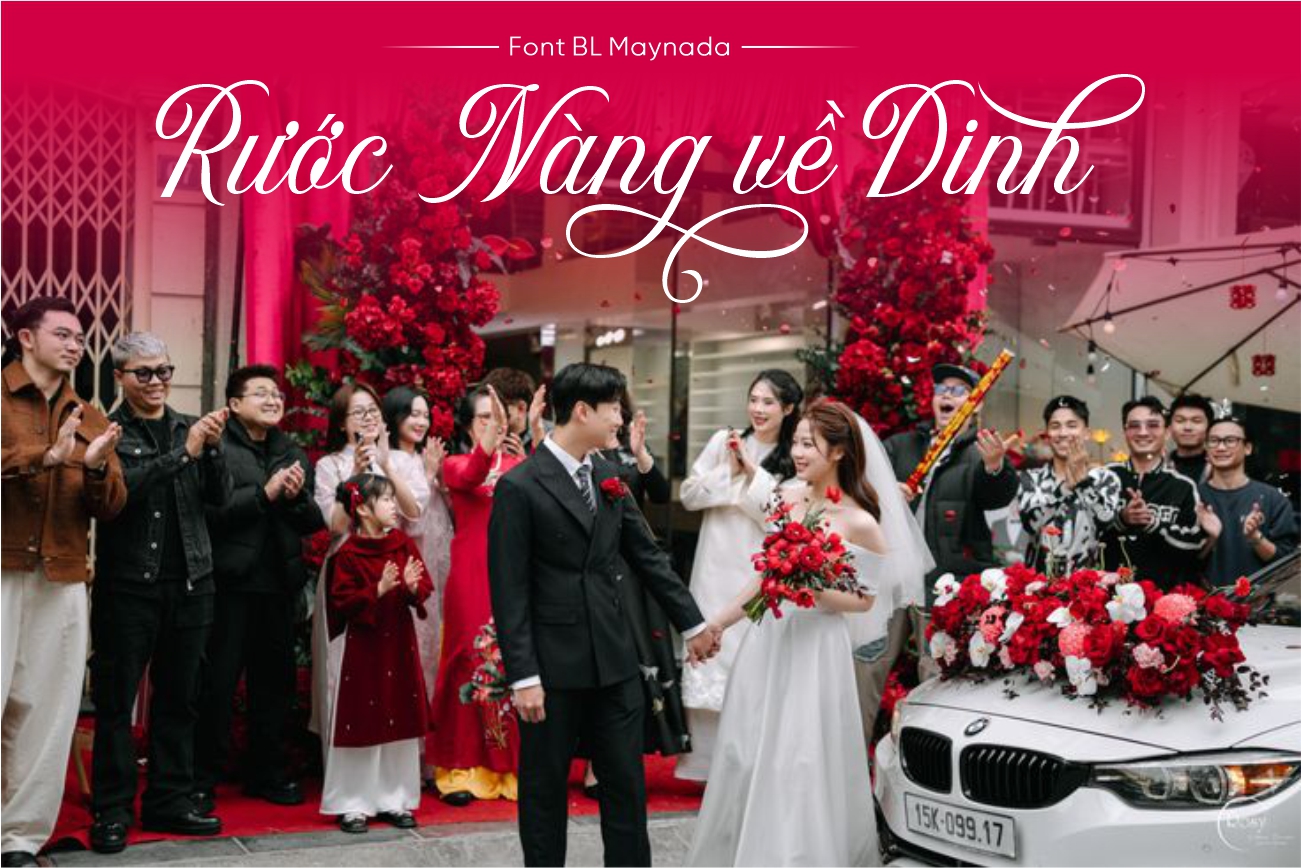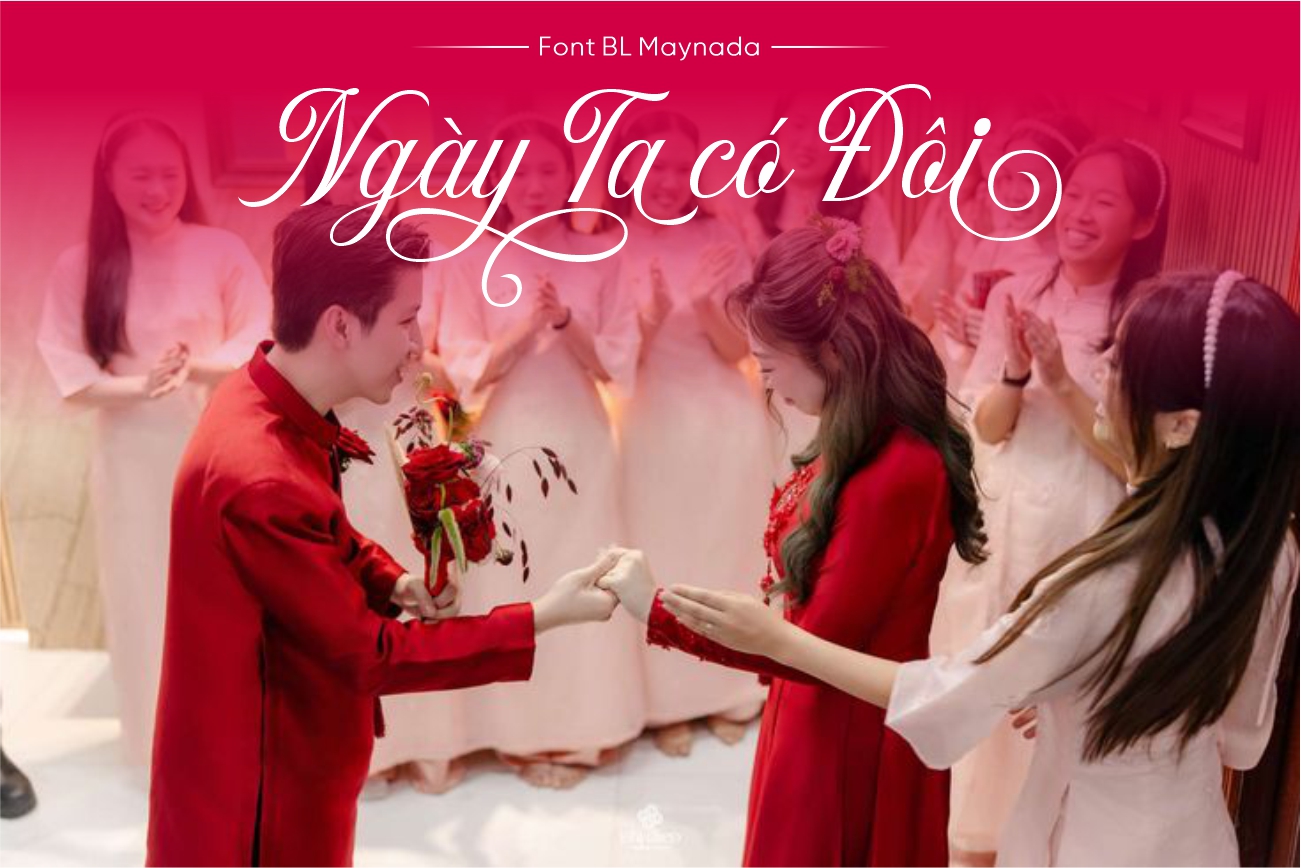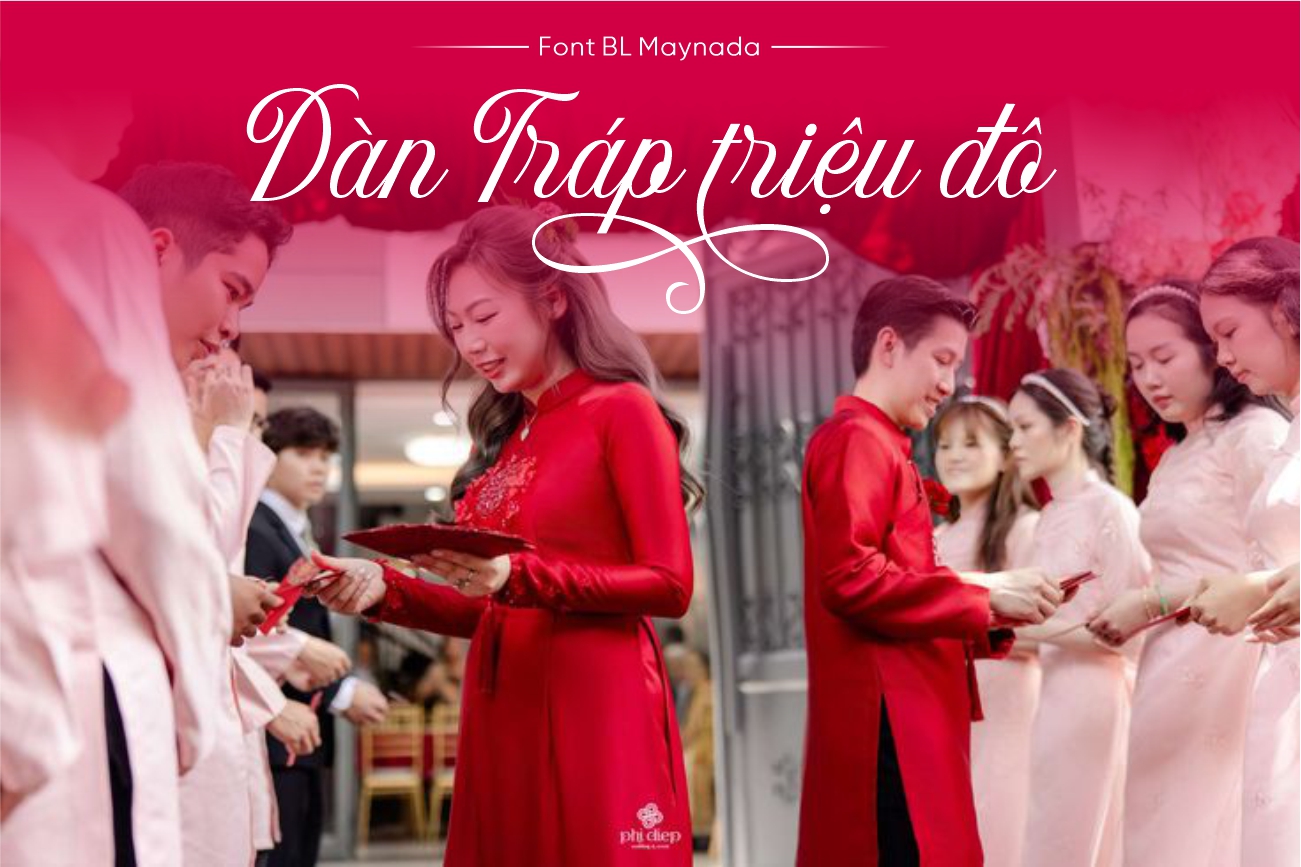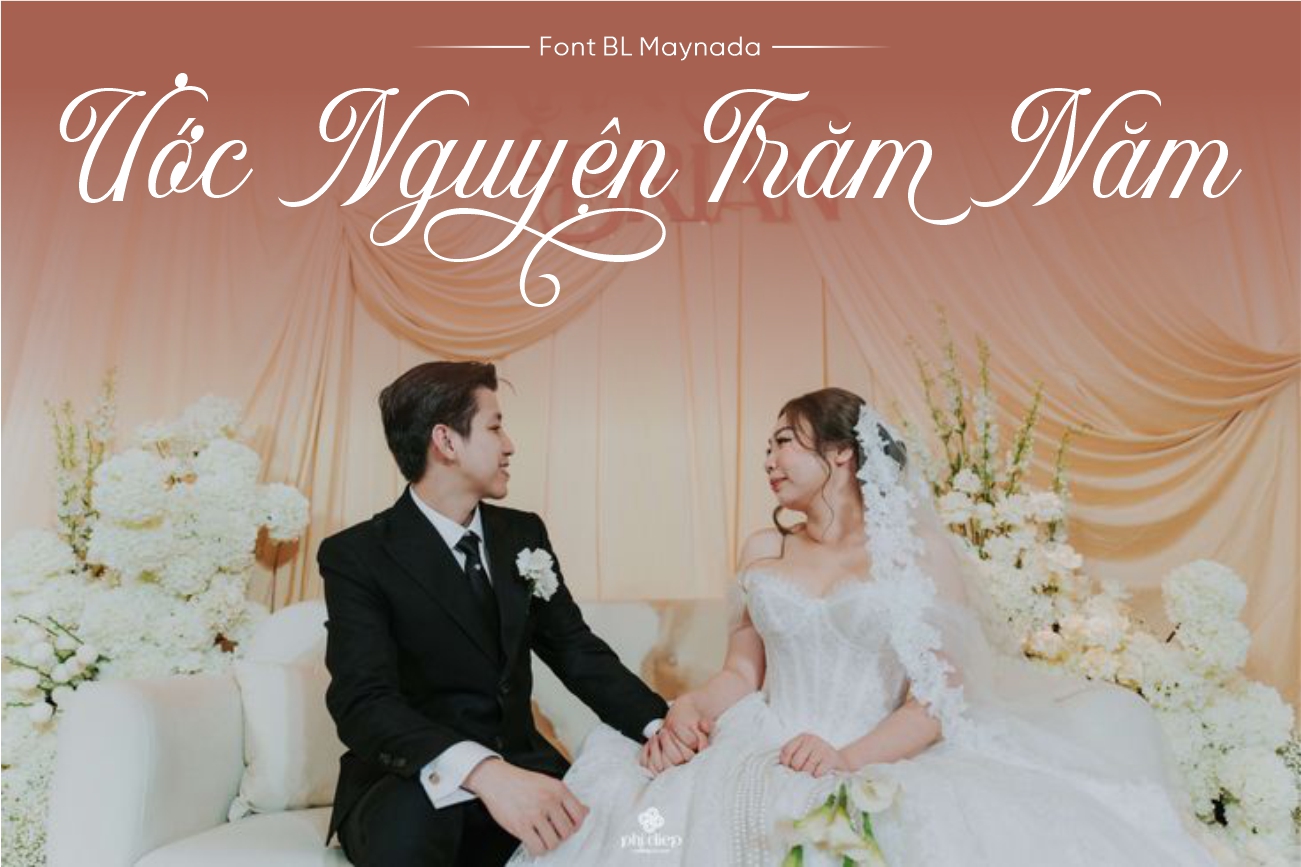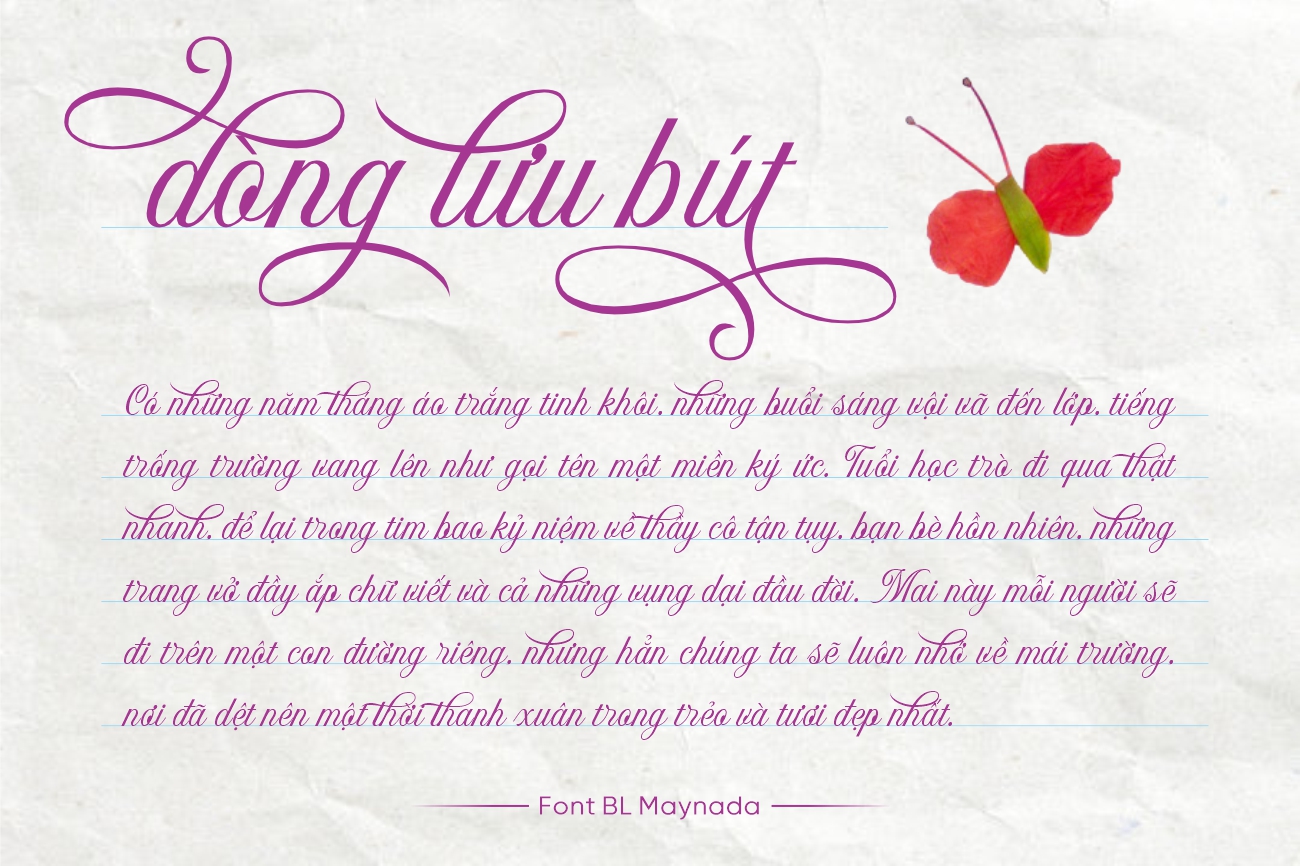
Font BL Maynada – Font Chữ Cho Thiệp Cưới Và Ảnh Cưới Lãng Mạn
Font BL Maynada là phiên bản Việt hóa hoàn chỉnh của phông chữ Maynada Script, được team BL tỉ mỉ Việt hóa với đầy đủ dấu tiếng Việt, giữ trọn vẹn tinh thần mềm mại, uyển chuyển vốn có của bản gốc. Với đường nét bay bổng, thanh mảnh nhưng dứt khoát, BL Maynada mang đến cảm giác vừa sang trọng, vừa ngọt ngào – rất lý tưởng cho các thiết kế wedding, thiệp cưới, thiệp mời, thiệp báo hỷ hay các bộ ảnh cưới nghệ thuật.
Font được thiết kế theo phong cách chữ viết tay calligraphy với những nét lượn tinh tế, phần đầu và đuôi ký tự kéo dài duyên dáng, tạo nên hiệu ứng mềm mại và nữ tính. Khi đặt trong các thiết kế thiệp cưới hoặc banner sự kiện, BL Maynada giúp nổi bật thông điệp tình yêu, tạo cảm giác trang trọng, tinh tế và đầy cảm xúc.
Không chỉ phù hợp cho các ấn phẩm đám cưới, BL Maynada còn được nhiều designer sử dụng trong album ảnh cưới, thiệp cảm ơn, poster chụp ảnh cưới, hay logo tiệm áo cưới, studio wedding. Font này thể hiện hoàn hảo tinh thần lãng mạn, sang trọng và đậm chất nghệ thuật – yếu tố quan trọng trong ngành cưới hỏi hiện đại.
Điểm nổi bật của font BL Maynada:
• Nét chữ mảnh, uyển chuyển, có các đường flourish trang trí đặc trưng của thư pháp hiện đại.
• Hỗ trợ đầy đủ tiếng Việt có dấu, phù hợp cho mọi nhu cầu thiết kế tại Việt Nam.
• Lý tưởng cho thiệp cưới, ảnh cưới, slogan tình yêu, backdrop đám cưới, poster và branding studio wedding.
Nếu bạn đang tìm một kiểu chữ mang đậm chất romantic calligraphy để tôn lên vẻ đẹp tinh tế và ngọt ngào trong các thiết kế thiệp cưới hay ảnh cưới, BL Maynada chính là lựa chọn hoàn hảo – vừa mềm mại, vừa thanh lịch, và chứa đựng trọn vẹn cảm xúc của ngày trọng đại.